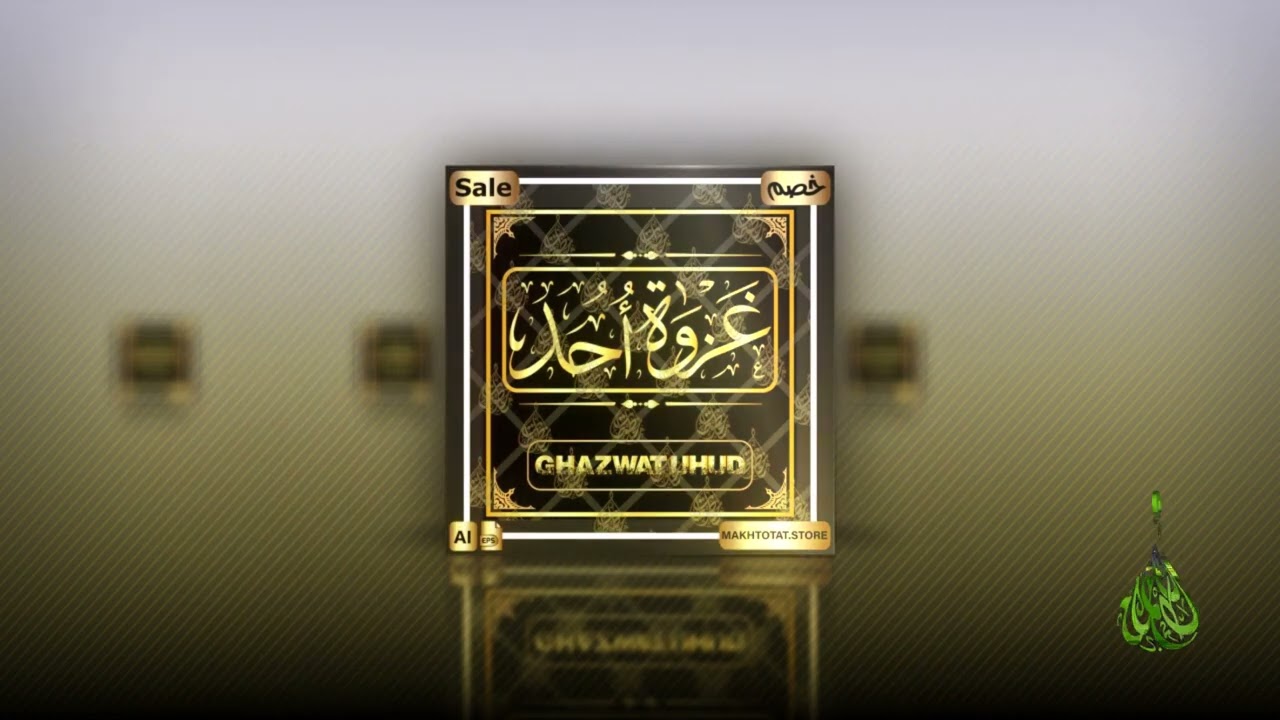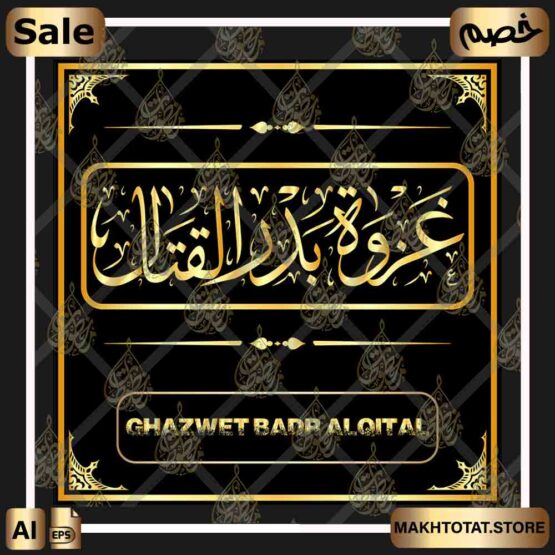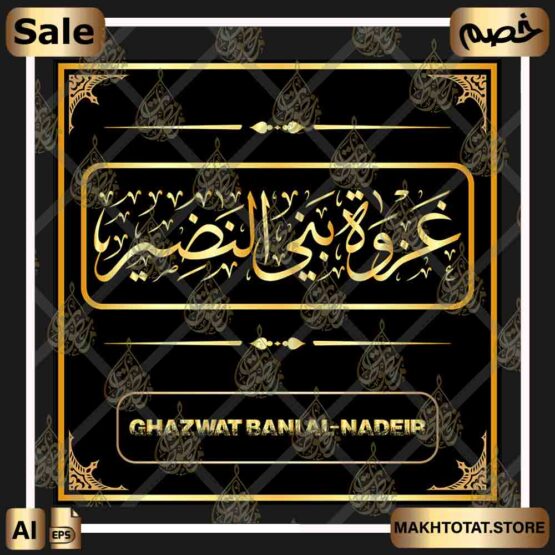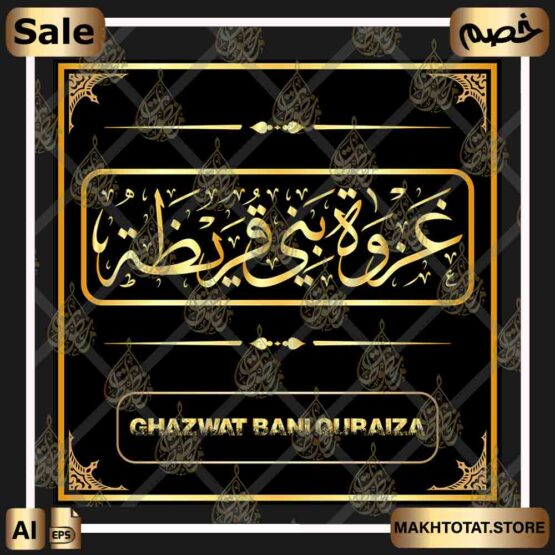
أسماء الغزوات بخط الثلث The Names Of Ghazawat in Thuluth Font
حزمة مخطوطات أسماء غزوات النبي ﷺ (The Prophet’s Battles) بخط الثلث – ملفات فيكتور (Vector EPS) للكتب التاريخية واللوحات قوالب فيكتور بصيغة EPS لعدد 43 مخطوطة لأسماء الغزوات بخط الثلث:
الإستخدامات المختلفة لمخطوطات أسماء غزوات النبي صلى الله عليه وسلم بخط الثلث:
برنامج مرئي عن غزوات الرسول صلى الله عليه وسلم.
مقال نصي عن إحدى غزوات الرسول صلى الله عليه وسلم.
غلاف كتاب عن غزوات النبي صلى الله عليه وسلم.
2- مجموعة مخطوطات أسماء الغزوات بخط الثُلث ربما تجد بها إسمين أو أكثر لنفس الغزوة ،مثل بدر الكبرى وبدر القتال ،فكلاهما نفس الغزوة أو الخندق والأحزاب أو غزوة الأبواء فهي ذاتها غزوة ودّان ،وتم جعل كل إسم بملف مخطوطة مستقلة ،حتى بلغ عدد المخطوطات بهذه المجموعة 43 مخطوطة.
بعض من أشكال مخطوطات أسماء الغزوات بخط الثلث The Names Of Ghazawat in Thuluth Font
أسماء الغزوات الموجودة بخط الثلث في هذه المجموعة التصميمية.
1- غزوة ودَان
2- غزوة ذي أمر
3- غزوة بني النضير
4- غزوة دومة الجندل
5- غزوة بني لحيان
6- غزوة خيبر
7- غزوة قرارة الكُدر
8- غزوة الكُدر
9- غزوة الفُرع
10- غزوة الغابة
11- غزوة الأبواء
12- غزوة سفوان
13- غزوة المريسيع
14- غزوة مؤتة
15- غزوة تبوك
16- غزوة بواط
17- غزوة بحران
18- غزوة الأحزاب
19- غزوة الخندق
20- غزوة ذي قرد
21- غزوة فتح مكة
22- غزوة الفتح
23- غزوة ذي العشيرة
24- غزوة أحد
25- غزوة بدر
26- غزوة بدر الكُبرى
27- غزوة بدرالقتال
28- غزوة بدر الآخرة
29- غزوة بدر الثانية
30- غزوة بدر الموعد
31- غزوة بني قريظة
32- غزوة الحديبية
33- غزوة ذات الرقاع
34- غزوة حنين
35- غزوة حمراء الأسد
36- غزوة بني المصطلق
37- غزوة الطائف
38- غزوة بني سليم
39- غزوة بني قينقاع
40- غزوة السويق
41- غزوة أنمار
42- غزوة أوطاس
43 غزوة هوازن